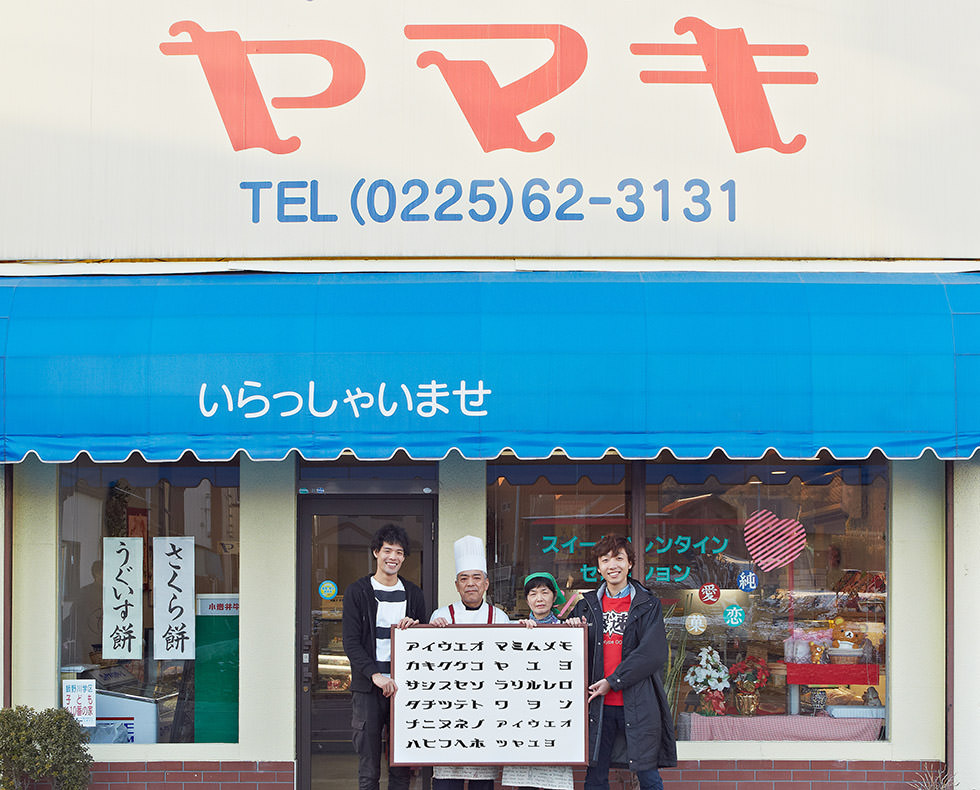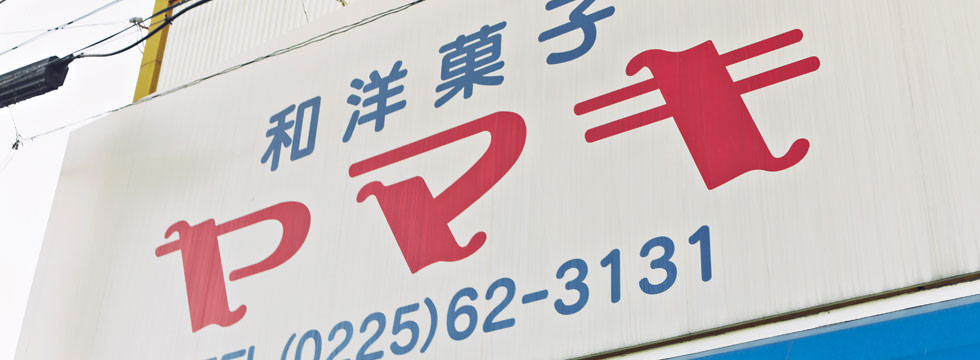
ヨーロッパ的なものに対する憧憬と時代の雰囲気が文字の装飾のディティールに現れていて、そこに懐かしさを感じる。ぽってりとした形が愛らしい。
「ヤマキ和洋菓子店」は1977年に創業した和洋菓子店。現店主の山崎さんは二代目だ。山崎の「山」と初代店主の名前に使われている「喜」の文字とを合わせて「ヤマキ」という屋号になったそうだ。書体をデザインしたのは当時地元の印刷会社に務めていたデザイナー。70歳を超えた今でも現役で仕事をされている。震災後、やはりお客さんは少なくなったそうだが、次の10年はまだ頑張るという山崎さんは言う。「やっぱり食べてくれる人が、これ普通のお店に売ってないなとか、もう一回食べてみたいなとか、誰か友達にあげてみたいとか、そこまでいけるようなお菓子作りをしたい。うーん…ちょっと時間はかかるんですけど。ゆっくり時間かけて一品だけ、色んなものをやらないで、この一品というお菓子を作りあげたいです。
Yamaki Confectionary Shop” was established in 1977. The current owner, Mr. Yamazaki, is the second generation. The name “Yamaki” is a combination of words for “YAMA” in “YAMAZAKI” and the character for “KI” used in the first owner’s name. The typeface was designed by a designer who was working for a local printing company at the time, and he is still working in his profession at over 70 years of age. After The Great East Japan Earthquake, the number of customers has also decreased, but Mr. Yamazaki said he will continue to work hard for the next 10 years. “I want to make sweets that people who eat them will say, it can’t be found in others, or want to try them again, or want to give them to friends. Well...it takes time. I want to take my time and make just only one unique product, without trying many different things, and I want to make just only one unique confection.